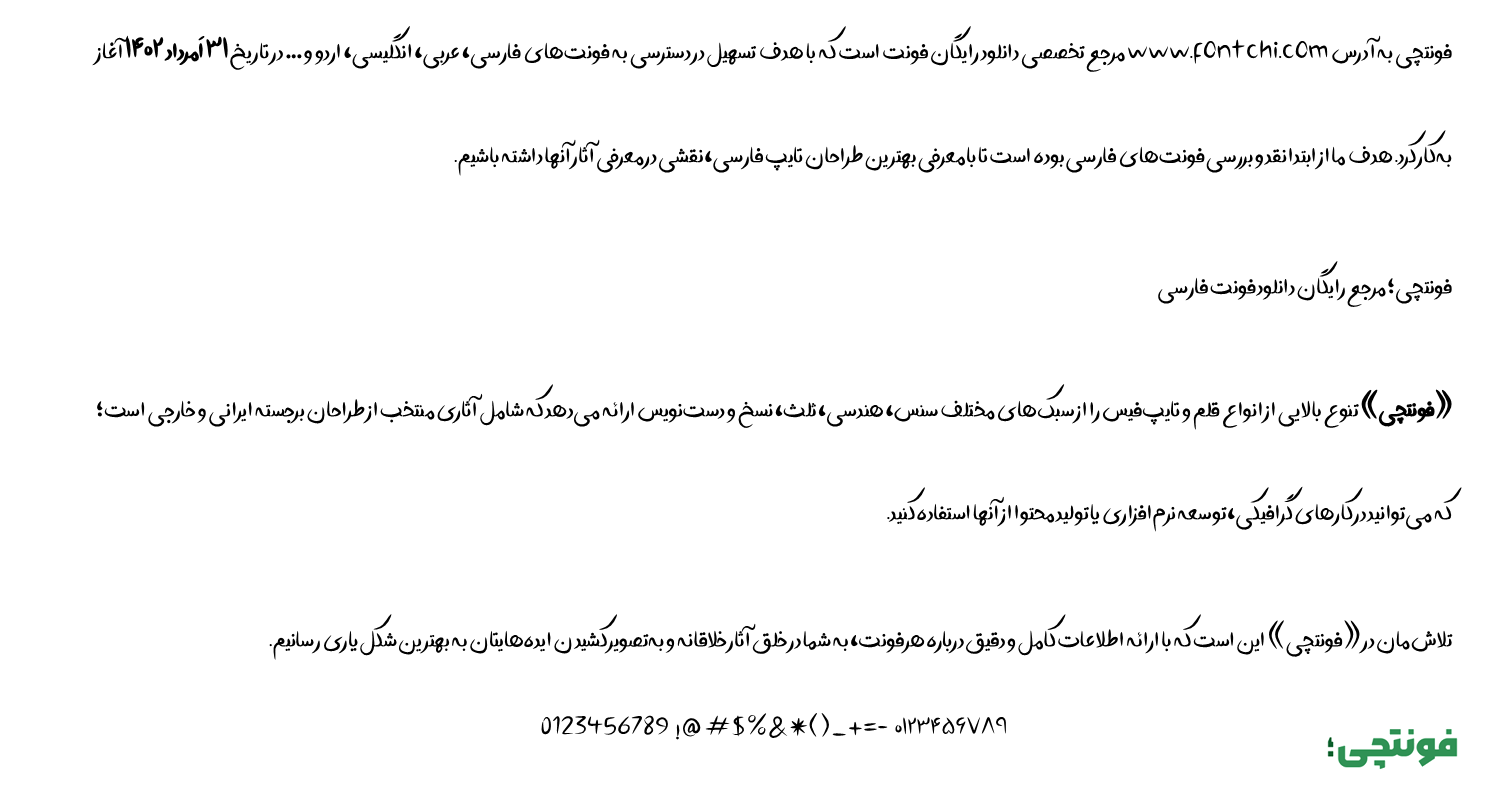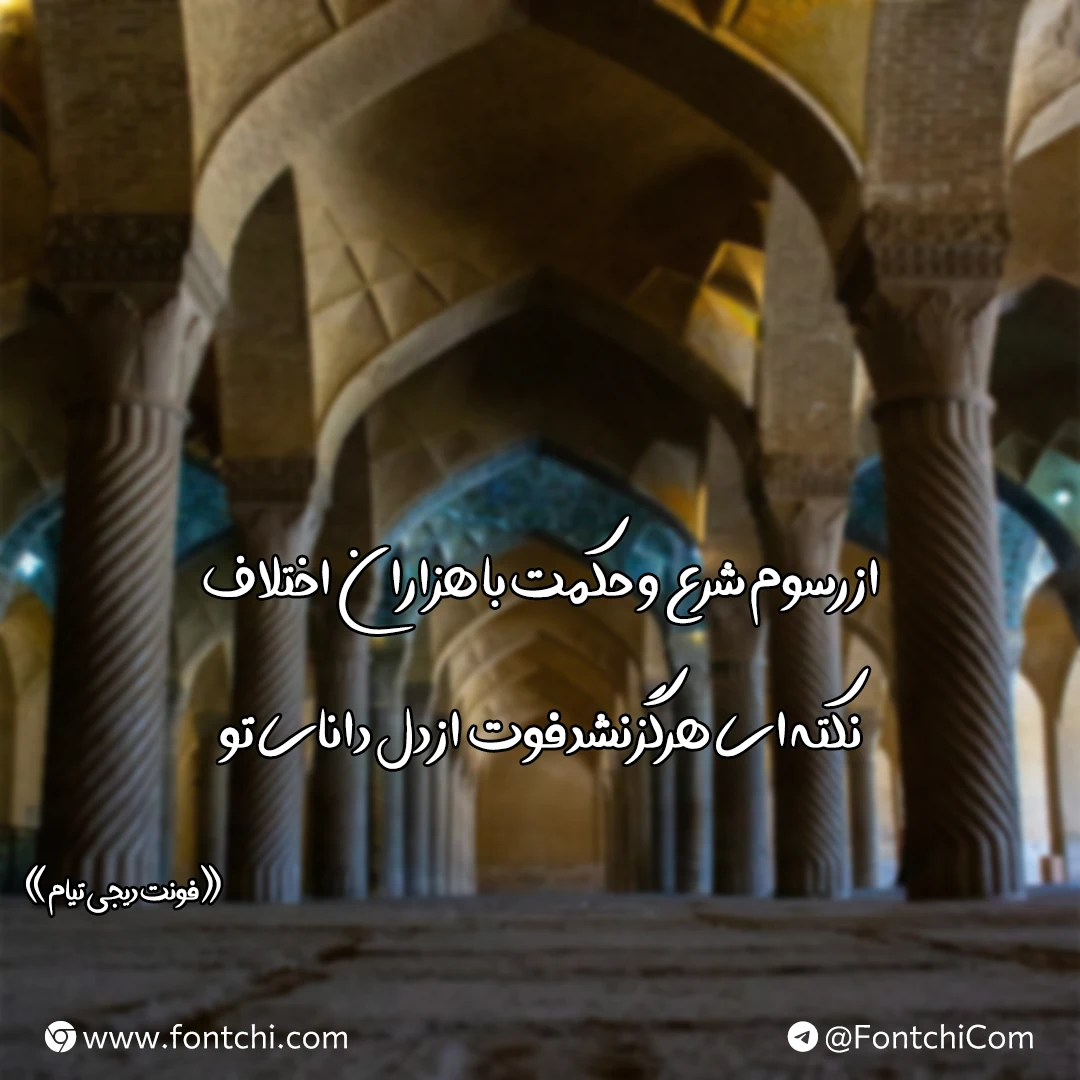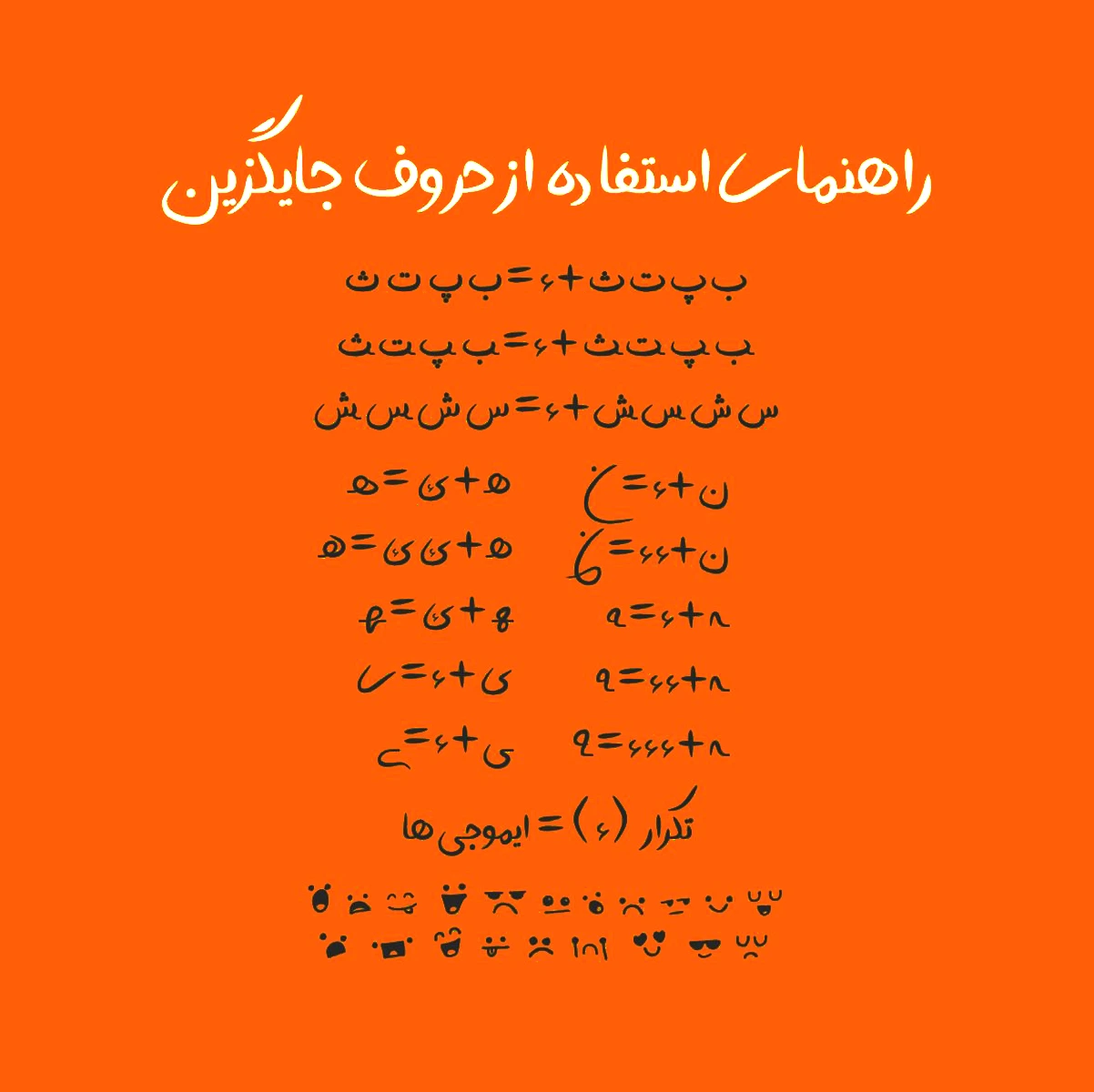
فونت تیام (Digi Tiam)
فونت دیجی تیام یا فونت تیام (به انگلیسی: Digi Tiam) قلمی دستنویس به سبک قلمویی است که بر اساس خط فهیمه نعمتاللهی طراحی شده است. این فونت با ظاهر براش خود برای استفاده در متونی که نیاز به صمیمیت و ایجاد ارتباط نزدیک با مخاطب مورد نیاز است توصیه میشود.
فونت دیجی تیام توسط مهدی برقگیر طراحی شده است و در کنار ترکیبات مختلفی که برای حروف جایگزین در خود دارد، با تایپ کاراکتر «ء» به تعداد بین ۲ تا ۲۱ بار، شکلکهایی به صورت اموجی نیز تایپ خواهد شد. از این رو برای استفاده در تصاویر عکسنوشته عالی است.
فونت دیجی تیام از زبانهای فارسی، عربی، انگلیسی و کردی پشتیبانی میکند. با توجه به ساختار رسمخط فارسی، از این فونت با یک سری محدودیتها میتوان در سایر زبانها همچون اردو نیز استفاده کرد.
تنها کاستی از نظر زبانی، عدم استفاده از حروف استاندارد عربی است که اعداد «٠٤٥٦» به صورت عدد فارسی «۰۴۵۶» تایپ میشوند. در بخش اعراب و کاراکترهای خاص نیز همنشینی گلیفها به خوبی رعایت شده است. با اینکه فونت تیام وزن متوسط (Medium) را دارد، ایراد جزئی آن ابعاد کوچکتر حروف نسبت به سایر فونتها است که باید از اندازه بزرگتر از حالت عادی برای متن استفاده کنید.
فونت تیام با حال و هوای دوستانهای که دارد برای استفاده در متون کوتاهی که در قالب عکسنوشته، اشعار، پست شبکههای اجتماعی و طراحی عناوین بر روی جلد کتاب و مجلات مناسب است.
راهنمای استفاده از حروف جایگزین فونت دیجی تیام
یکی از قابلیتهای این فونت پشتیبانی از حروف جایگزین است که میتوانید با فشردن کاراکتر «ء» در انتهای حروفی مانند «ب، پ، ت، ث، س، ش، ن، ه، ی» این حروف را مانند تصویر زیر با حالت مختلفی تایپ کنید. استفاده از این حروف جایگزین به زیباتر و نمایشیتر کردن فونت شما کمک میکند.
قابلیت دیگر این فونت تایپ ۲۰ اموجی مختلف است که با تکرار کاراکتر «ء» پشت سر هم، میتوانید آنها را مانند تصویر بالا تایپ کنید.